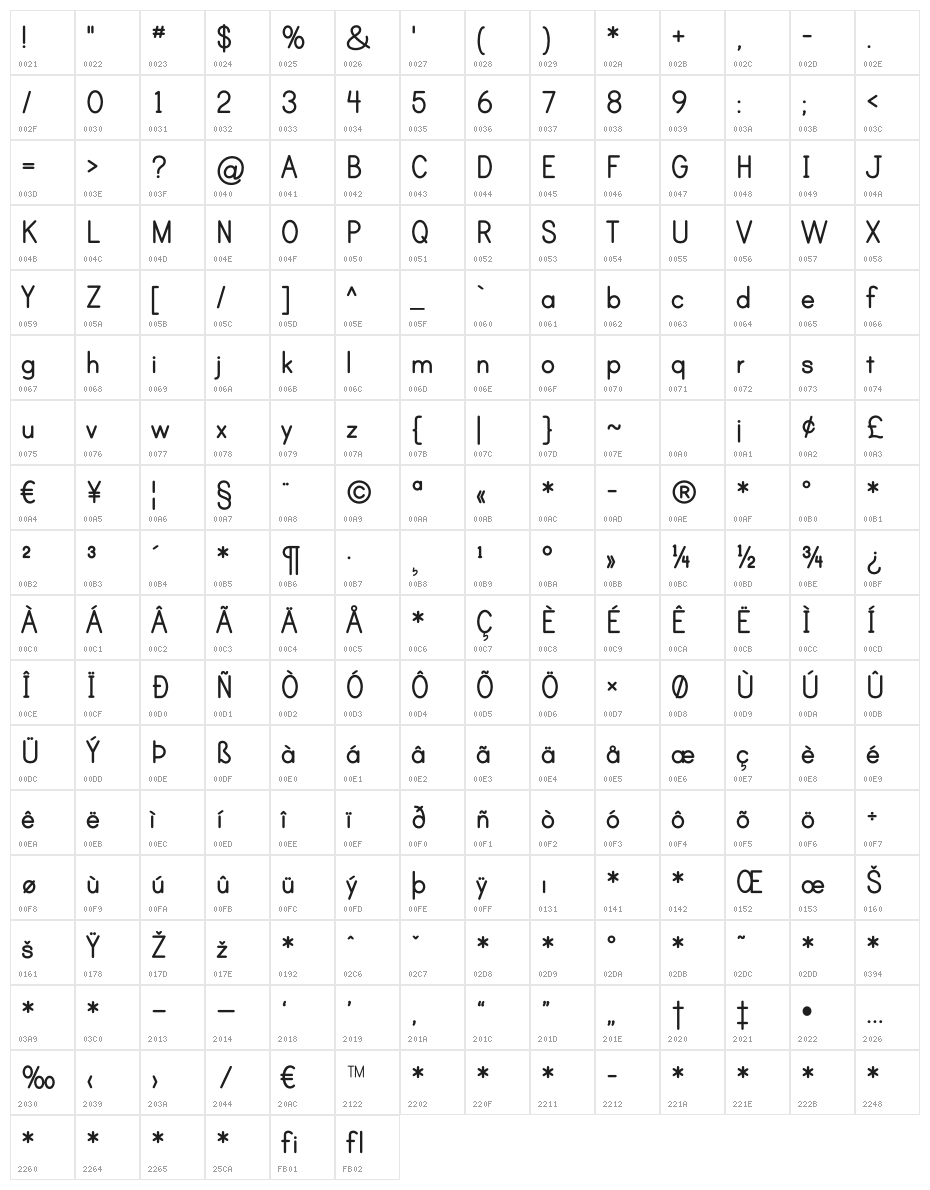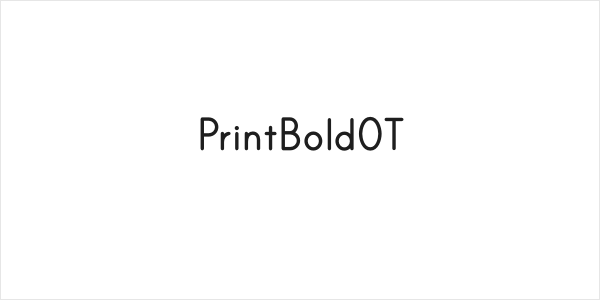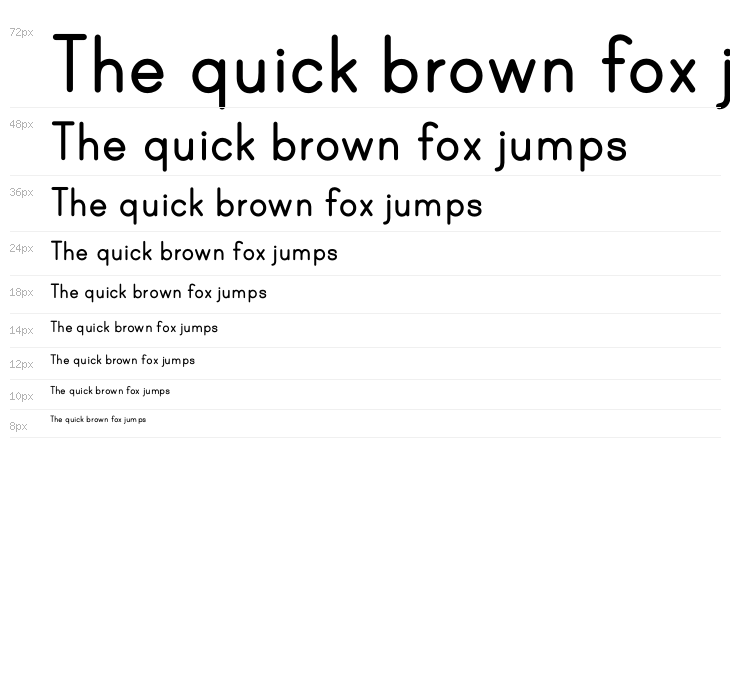
PrintBoldOT Font
| Progetti proposti | Ideal for branding, advertising, web design, and user interfaces where a modern and approachable look is needed. |